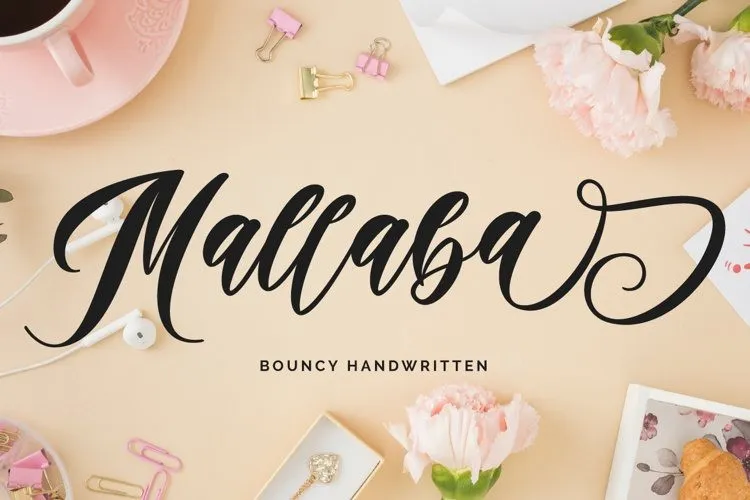
A Mallaba Font é uma nova tipografia romanceada com toques suaves e encantadores que adicionarão beleza e elegância a qualquer design. Feita para 99designs, essa fonte será um brilho extra no seu trabalho de criação, dando maior valor à sua ideia. Seja ela branding, citações ou qualquer outro tipo de projeto gráfico — a Mallaba Font enriquecerá seu trabalho, oferecendo uma paleta de opções para que você possa expressar suas ideias de maneira única e poderosa. É ideal tanto para designers como para quem busca um estilo encantador em seus projetos visuais.